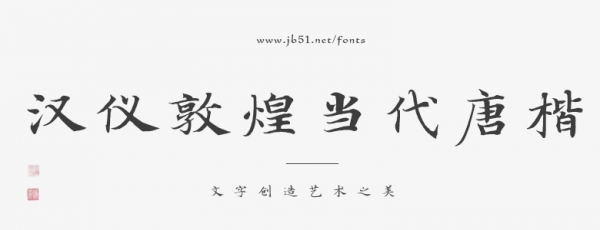
汉仪敦煌当代唐楷秉持“修旧如旧”的设计理念,在保留底本笔触与书写风格的基础上,适当提升一致性,着重呈现隶书楷化过程中逐渐成熟、规范化的书写特征,既还原了敦煌写经的原生气质,也满足现代用字需求。
汉仪敦煌当代唐楷整体风格端庄静雅、严谨规范,在规范用字与古籍原貌间取得平衡,使千年写经艺术在当代得以传承,搭建起大众与敦煌文化的沟通桥梁。该字体广泛适用于唐代文史专题出版物、佛学典籍刊印复刻、唐代题材影视物料、唐风国潮品牌视觉、敦煌地域伴手礼包装等多元场景,以兼具骨力与温度的笔墨气韵传递东方书法之美,满足对传统文化与当代设计融合的多元审美需求。